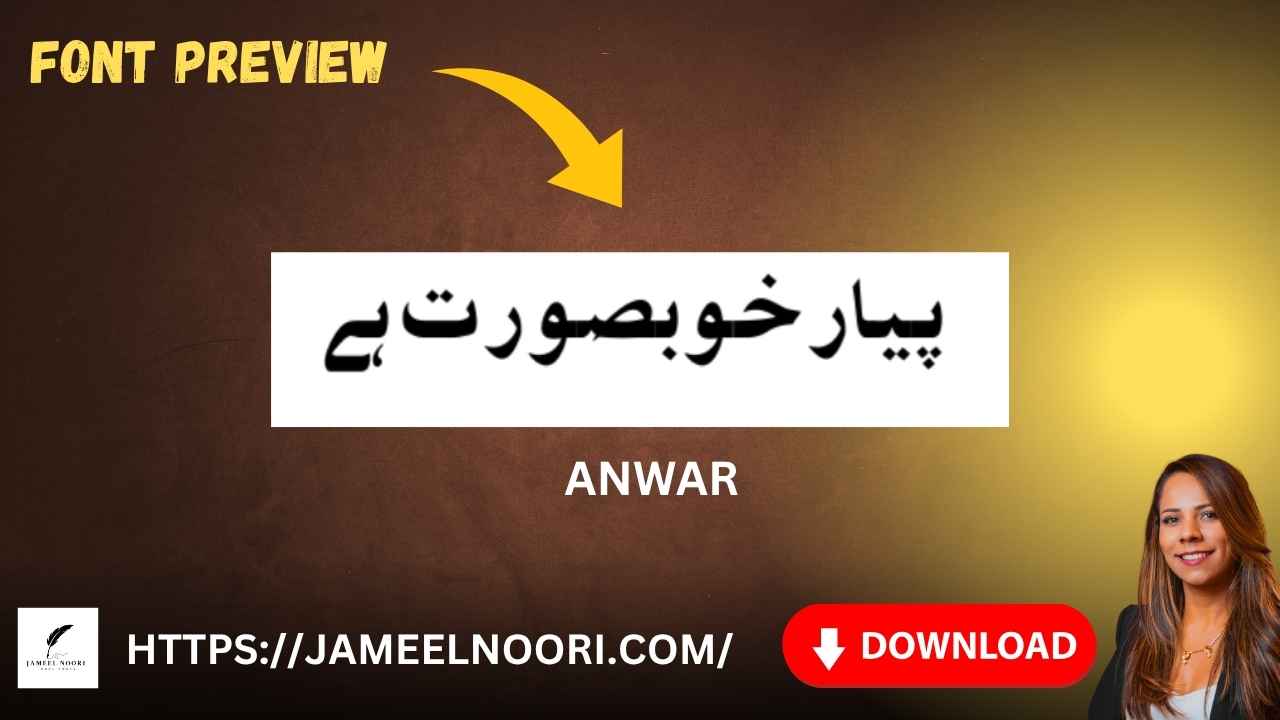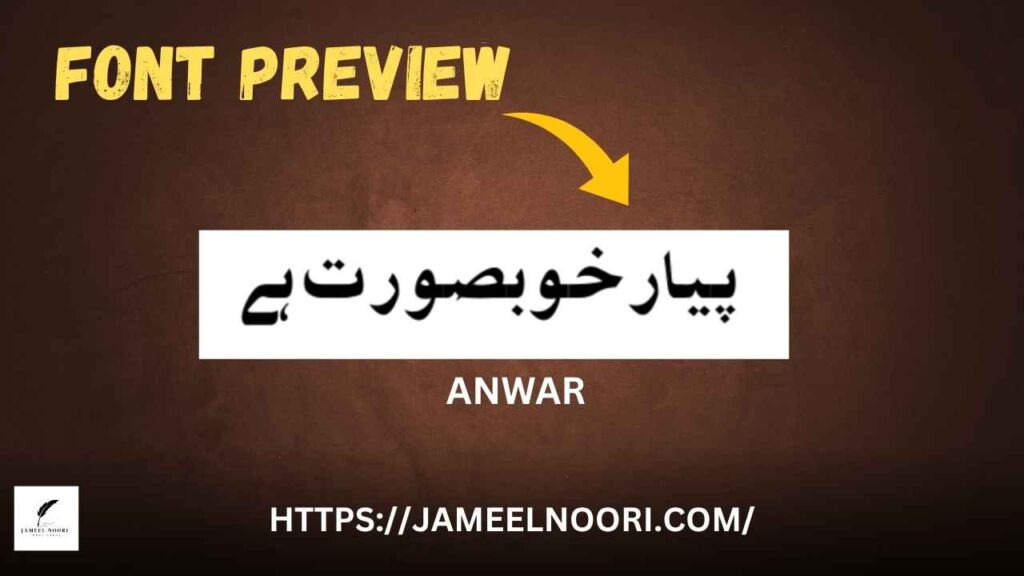
Introduction – Anwar Urdu Font Download
Agar aap Urdu design projects ke liye ek stylish aur readable font dhoondh rahe hain to Anwar Urdu Font aapke liye best choice ho sakta hai. Ye ek TrueType Font (TTF) hai jo designers aur Urdu lovers ke darmiyan kaafi mashhoor hai. Iska simple aur elegant style isay print aur digital designs dono ke liye ideal banata hai.
Features of Anwar Font
✅ Perfect for headlines & body text
✅ Stylish curves and clean letters
Use Cases of Anwar Font
- 📚 Urdu books layout
- 📰 Newspaper or article headlines
- 📱 Mobile apps & websites
- 🎨 Graphic design posters
- 📝 Urdu typing practice
Why Choose Anwar Urdu Font?
📌 Readable Design: Anwar font ki readability Urdu content ke liye ideal hai.
📌 Creative Look: Iska artistic look posters aur flyers ke liye bhi perfect hai.
Anwar Urdu Font ek khubsurat aur reliable choice hai un logon ke liye jo Urdu designing projects me high-quality aur stylish font dhoond rahe hain. Chahe aap social media post bana rahe hon, ya ek kitab ka layout design kar rahe hon – ye font har jagah perfect fit hota hai.
Frequently Asked Questions – Anwar Urdu Font Download
Anwar font kis tarah ka Urdu font hai?
Ye ek TrueType Urdu font hai jo stylish aur easy-to-read layout offer karta hai
Font me Urdu ke saare alphabets shamil hain?
Jee haan, tamam Urdu alphabets aur commonly used glyphs included hain